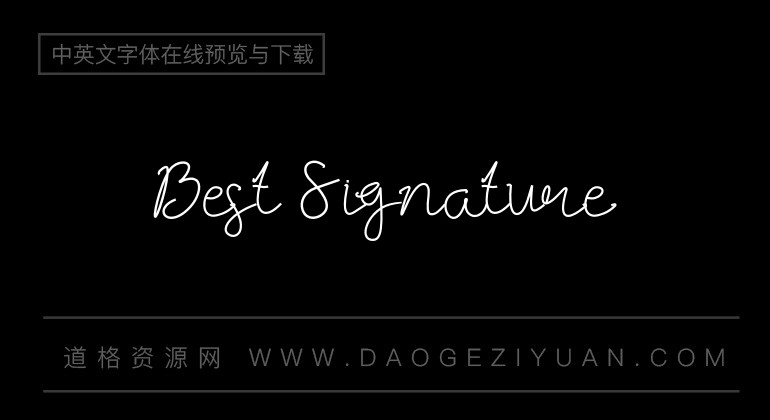
Best Signature
Best Signature 字体是一款设计精美的手写字体,它具有自然的手写体魅力,可以为您的设计提供独特的个性化风格。它的主要特点是每个字母都有自己的独特外观,并且它的笔画细节非常丰富,可以提供自然的手写效果。它还具有较高的可读性,可以使您的设计更加有趣且易于理解。
Best Signature是一款非常不错的手写艺术字体,具有很好的视觉感,适合于文化类的宣传设计、商业类品牌的广告和产品包装设计以及个性化文字排版等较多场景。